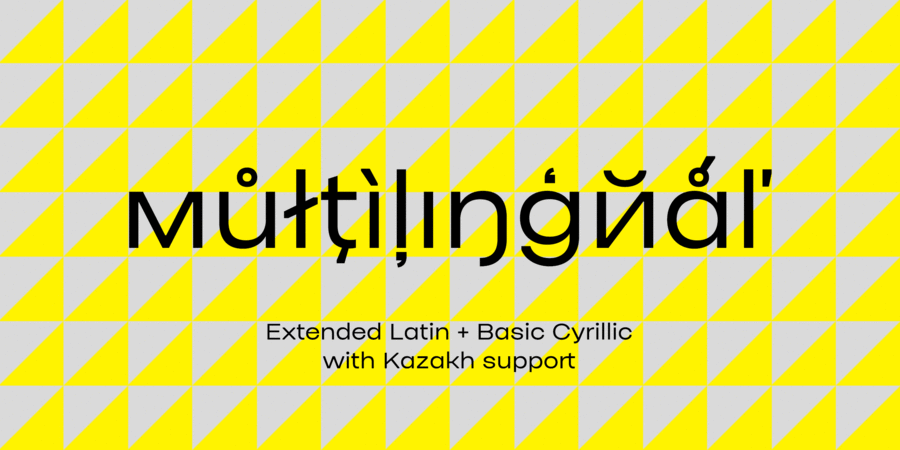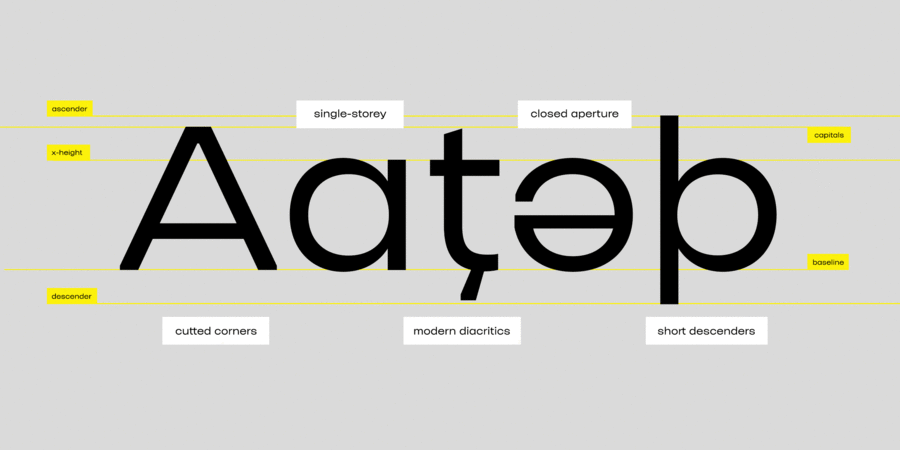
Гарнітура Ermilov Pro – це сучасний масивний геометричний гротеск зі спеціальними фасками в кутах літер. На його створення надихнули роботи українського художника-конструктивіста Василя Єрмилова. Першу версію Ermilov Bold створили Кирило Ткачов і Banda Agency для міжнародної маркетингової кампанії Ukraine NOW у 2018 році. Шрифт отримав друге дихання у 2022 році після початку повномасштабної російської війни в Україні. Для міжнародного спілкування розширені латинські символи були вкрай необхідні.
І нарешті, втретє, студія AlfaBravo повернулася до цього шрифту, щоб додати легкі накреслення, українські альтернативи, лігатури, і перетворити Ermilov на повноцінну гарнітуру для широкого спектру завдань – від обкладинок книг до вебсайтів. Шрифт розробили Кирило Ткачав і Сергій Макаренко у 2025 році. Світ ловив мене, та не спіймав!